I en verden, hvor digital kommunikation dominerer, kan den rette skrifttype forvandle en almindelig besked til et kunstværk. Blandt de utallige muligheder skiller de gotiske skrifttyper sig ud med deres dramatiske, historiske og ofte mystiske æstetik. De er ikke kun et levn fra fortiden, men et kraftfuldt værktøj til at skabe et unikt visuelt udtryk i dagens digitale landskab, hvad enten det er på din iPhone, Android-enhed, sociale medier eller i dine yndlingsspil. Denne dybdegående guide vil udforske gotiske skrifttyper, deres licensbetingelser, hvordan du kan anvende dem, og hvad der gør dem så særlige.
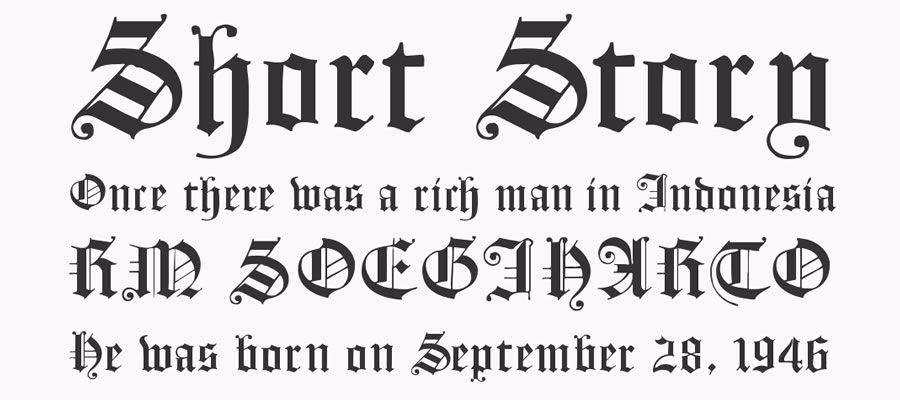
Gotisk skrift, ofte kendt som Blackletter eller Fraktur, er mere end blot en samling bogstaver; det er en kunstform, der daterer sig tilbage til middelalderen. Karakteriseret ved sine ofte tætte, vinklede og ornamenterede streger, fremkalder den en følelse af tradition, autoritet og en vis historisk tyngde. Oprindeligt udviklet i Europa, især i Tyskland og Skandinavien, blev gotisk skrift udbredt i manuskripter og tidlige trykte bøger. Dens komplekse og detaljerede former gjorde den ideel til religiøse tekster og officielle dokumenter, hvor æstetik og værdighed var altafgørende. I dag bruges den til at tilføje et strejf af nostalgi, mystik eller dristighed til moderne designs.
Gotisk Tekstgeneratorer: Skab Unikke Beskeder på Din Telefon
Mens installation af systemomfattende skrifttyper på mobile enheder som iPhones og Android-telefoner kan være begrænset eller kræve specifikke apps, er der en nem og effektiv måde at bruge gotisk tekst på: gotiske tekstgeneratorer. Disse onlineværktøjer er geniale, fordi de konverterer almindelig tekst til specielle Unicode-tegn, der ligner gotisk skrift. Det bedste er, at disse Unicode-tegn kan kopieres og indsættes overalt, hvor du normalt ville skrive tekst – uanset om det er en besked, en opdatering på sociale medier eller et brugernavn i et spil.
Forestil dig at give din Instagram-biografi, en TikTok-tekst, en WhatsApp-besked eller en Fortnite- eller Roblox-besked et middelalderligt eller dristigt twist. Det er præcis, hvad en gotisk tekstgenerator gør muligt. Processen er typisk meget ligetil:
Det er vigtigt at bemærke, at selvom disse Unicode-tegn fungerer på de fleste mobile platforme, kan visningen af nogle gotiske skrifttyper og bogstaver variere en smule på mobil i forhold til desktop. For den bedste oplevelse med at generere teksten anbefales det ofte at bruge en desktopbrowser.
Eksempler på Gotiske Tekststile via Generatorer
Gotiske tekstgeneratorer tilbyder ofte forskellige variationer af gotiske og beslægtede stilarter, som kan give dine beskeder et unikt præg:
- Gotisk: Tekst skrevet i 𝔊𝔬𝔱𝔥𝔦𝔠 𝔩𝔢𝔱𝔱𝔢𝔯𝔰.